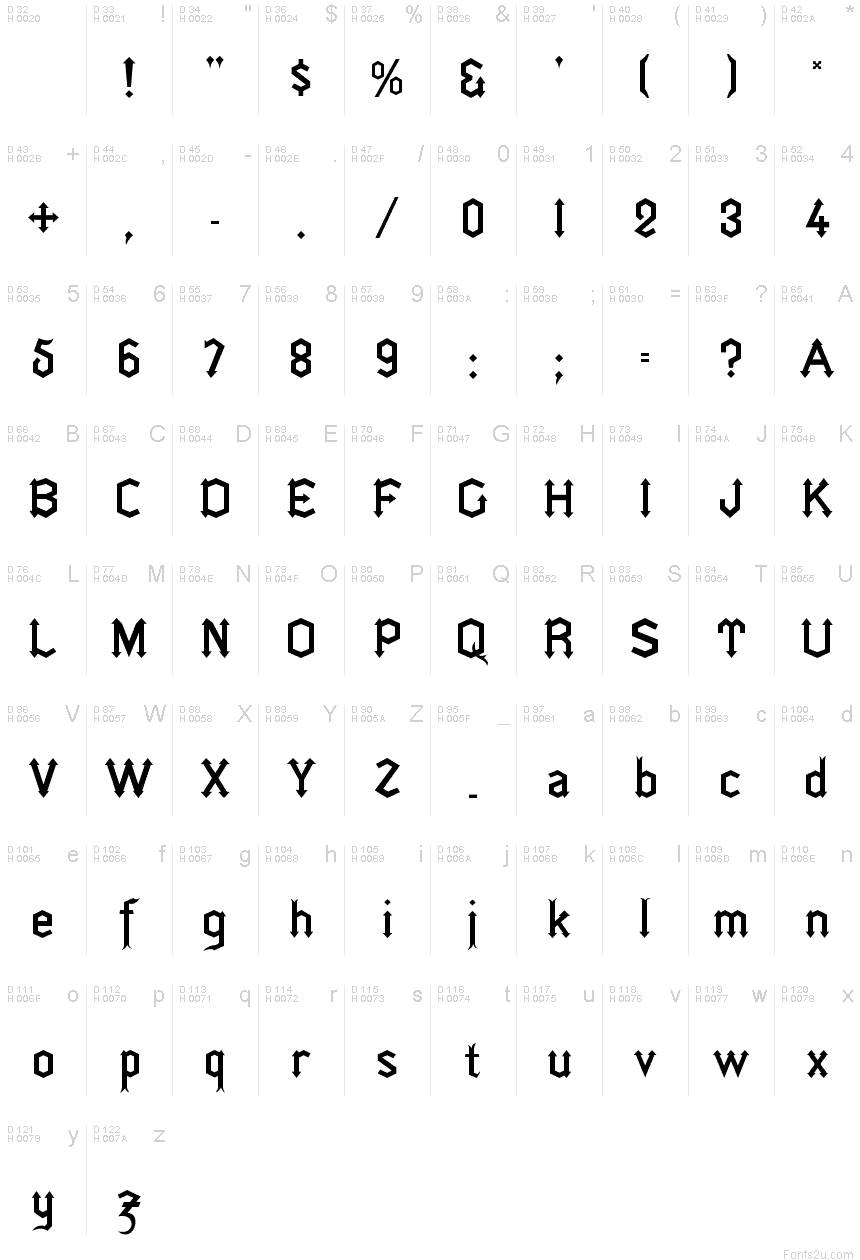
Arrowhead Lake to darmowy krój pisma typu display, inspirowany strzałkami. Ostre, trójkątne groty wieńczą litery, zmieniając ich szerokie, geometryczne kształty w powtarzalny system znaków kierunkowych. Kanciasta sylwetka jest wyrazista i niezaprzeczalna.
Sklep ze sprzętem outdoorowym lub ośrodek przygodowy mógłby zbudować swoją identyfikację wizualną wokół drogowskazowej konstrukcji tego kroju. Nadaje się on również na plakaty wydarzeń, grafikę gier i gadżety, gdzie kształty strzałek mogą służyć jako część emblematu, a nie zwykły napis. Jego najsilniejsze motywy to nawigacja, podróże po dzikiej przyrodzie i stylizowana przygoda pogranicza.
Based on Arrowhead from the Solotype Catalog and alphabet books. Scanned and created by Character. All rights waived.